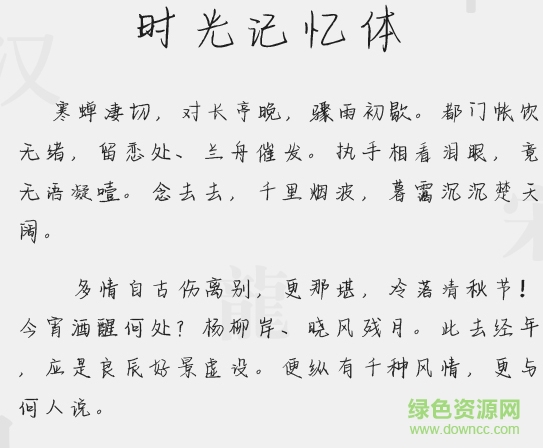
小米時光記憶字體
時光記憶.ttf是小米手機(jī)推出的一款藝術(shù)字體,字跡清秀婉約,柔和的筆觸讓你感受時光如水的靜靜流淌,造型干凈充滿靜好氣息,喜歡的朋友來綠色資源網(wǎng)下載體驗吧!
小米時光記憶字體介紹
時光記憶體是鋼筆書法字體,字跡清晰隨意,適合平面設(shè)計、廣告設(shè)計、海報設(shè)計等多種領(lǐng)域,讓你的文字具有不一樣的美感和視覺享受!